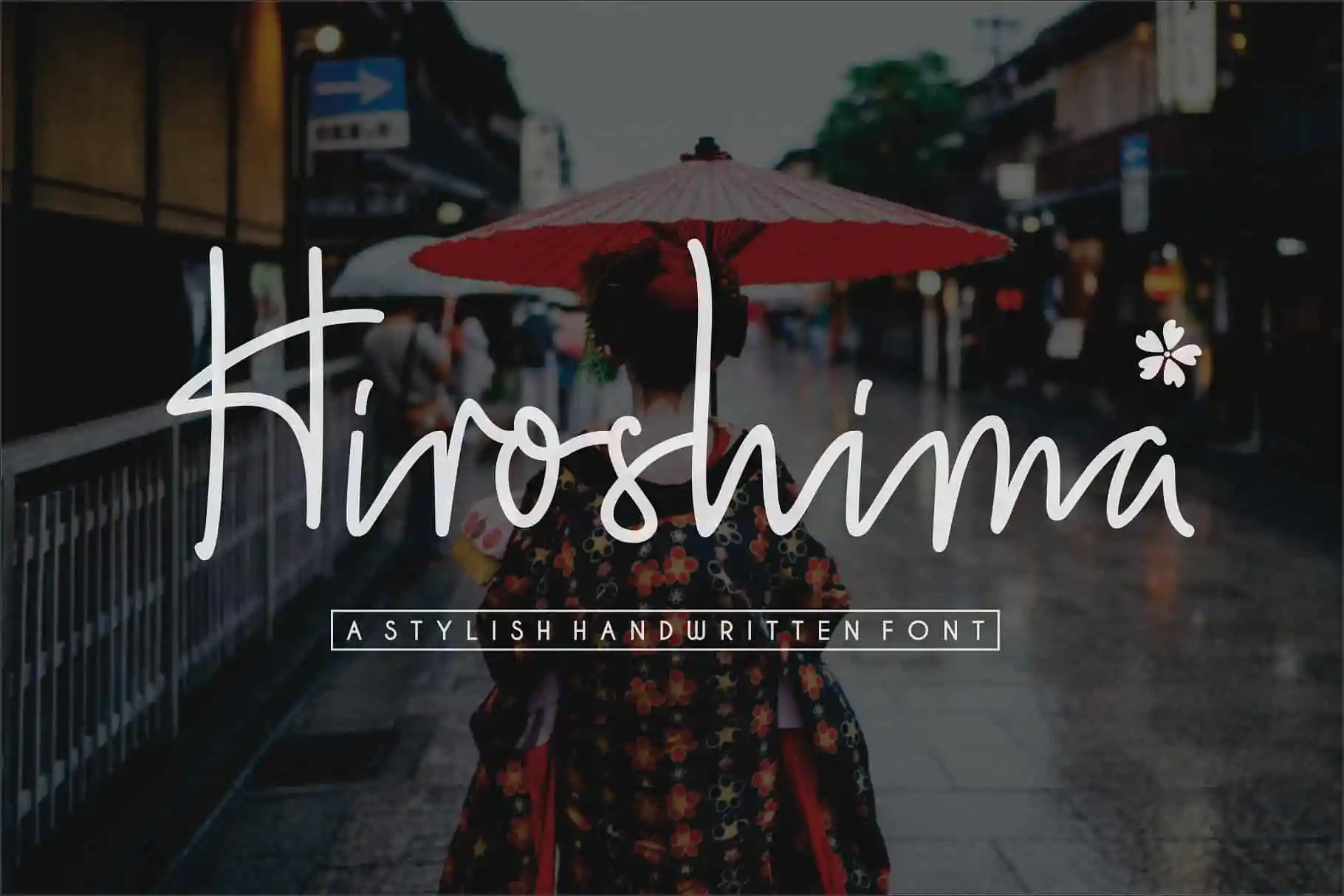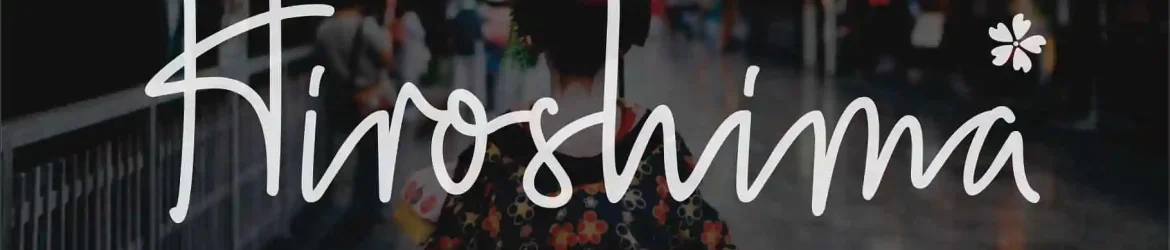
A fonte Hiroshima Script é uma escolha perfeita para quem procura uma mistura elegante e natural dos traços manuscritos, com linhas finas e grossas que a tornam ideal para diversos projetos. Com seu design cuidadosamente elaborado por Sronstudio, Hiroshima apresenta um estilo sofisticado e atemporal, perfeito tanto para uso em fotografias como para criar watermark, postagens de redes sociais, anúncios ou identidades visuais. Suas linhas estilizadas combinam com a delicadeza da escrita manuscrita, criando um contraste elegante que a torna perfeita para criações digitais que requerem um toque autêntico e pessoal. A Hiroshima é uma escolha ideal tanto para design de logotipos e identidade visual quanto para produtos, embalagens ou convites, garantindo que cada detalhe seja cuidadosamente pensado e executado. A fonte Hiroshima Script oferece a liberdade de personalizar e criar um estilo único, tornando-a uma opção confiável para projetos variados. Ela é perfeita para aqueles buscando expressar algo autêntico e original em suas criações digitais, seja ela na formatação de um post de rede social ou no design do seu próximo produto. Com essa fonte, você pode ter a sensação de um designer profissional sem o esforço adicional que requer criar todo o design por conta própria.